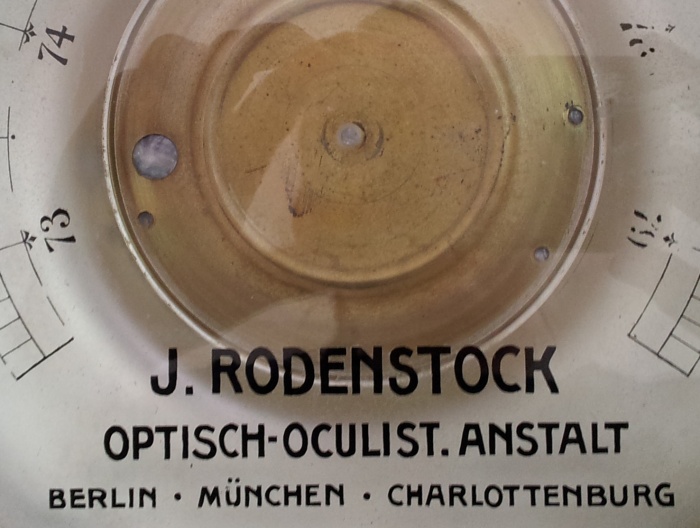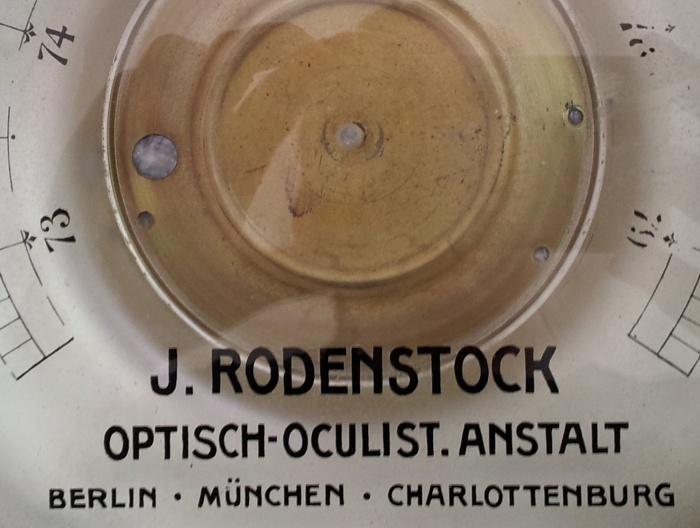
Serifenlose Jugendstil-Schrift?
Ich suche die beiden Schriften auf diesem Foto.
wirkt sehr handgemacht – aber vielleicht kennt einer von Euch einen passenden Font?
Das näheste, dass ich bisher gefunden habe, sind die Rennie Mackintosh-Fonts, die aber eben noch viel zu verschnörkselt sind.
Bei den Ziffern kommt die Didot italic von Linotype halbwegs ran, ist mir aber zu dünn und der dicke Querstrich vom Vierer fehlt ...
Ich pingelige hätt’ nur gern noch das A und das K :-)
Für das aktuelle Projekt wird die Schrift schon nachgebaut – aber grundsätzlich wüsste ich es gern, weil mir die serifenlose Jugendstil-Schrift (und ähnliche) schon zum dritten Mal unterkommt und ich mir denke, die muss es doch irgendwo geben!
Und die Ziffern finde ich traumhaft schön …
Ich finde, die Stocklet geht ganz gut – da passt das A wunderbar.